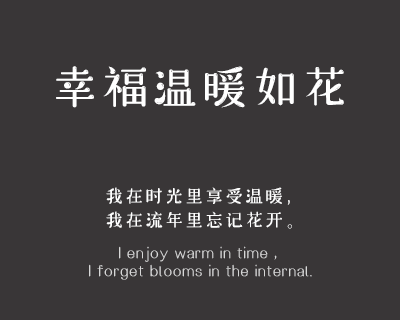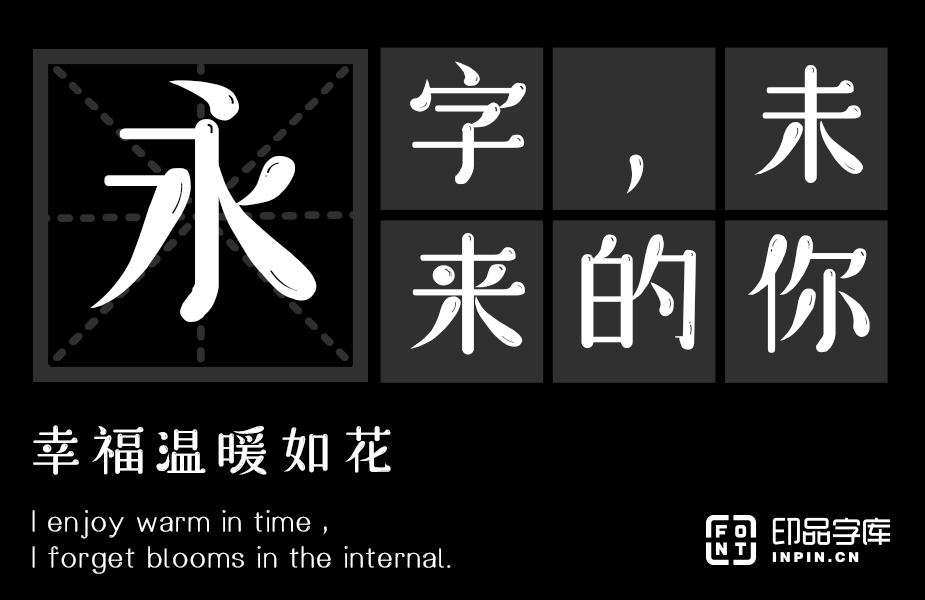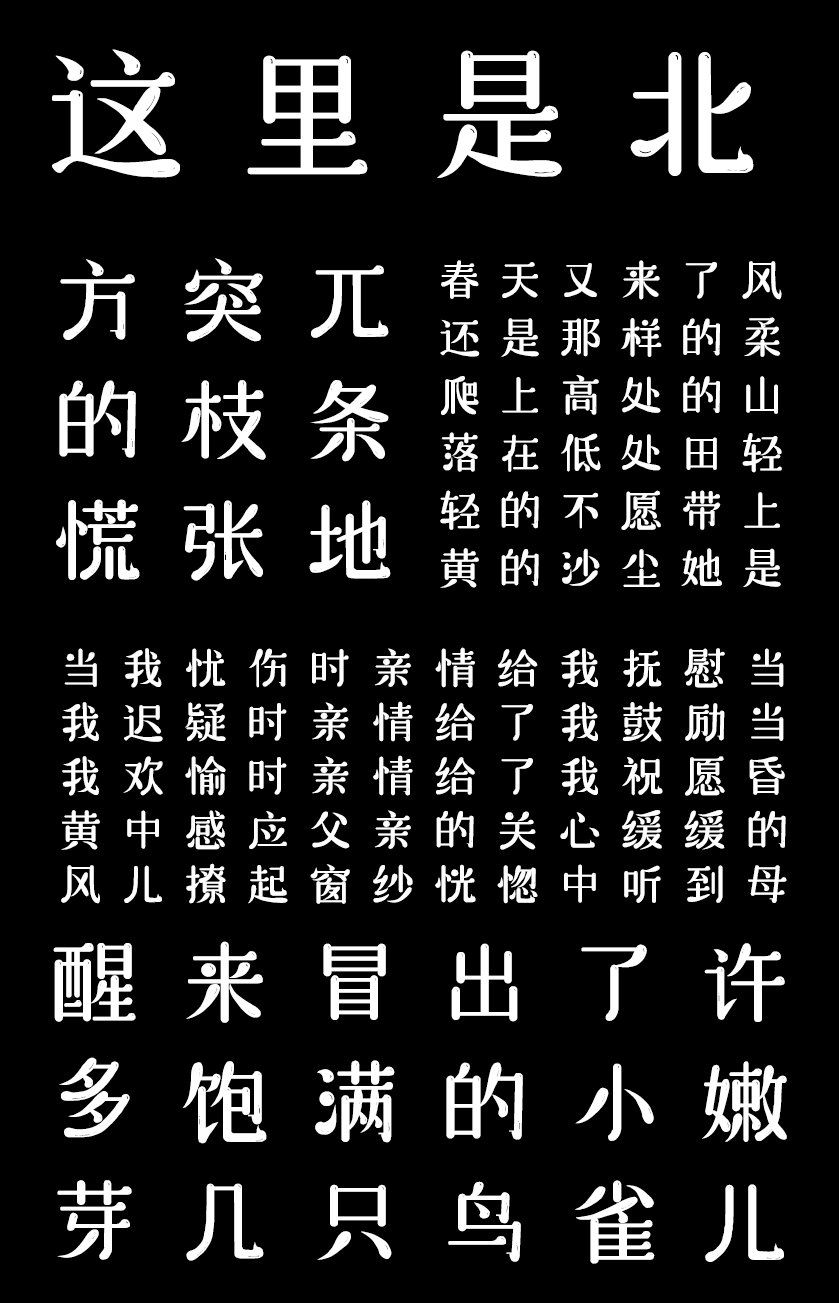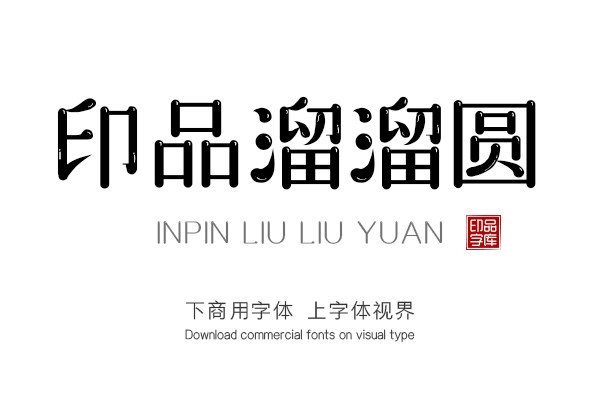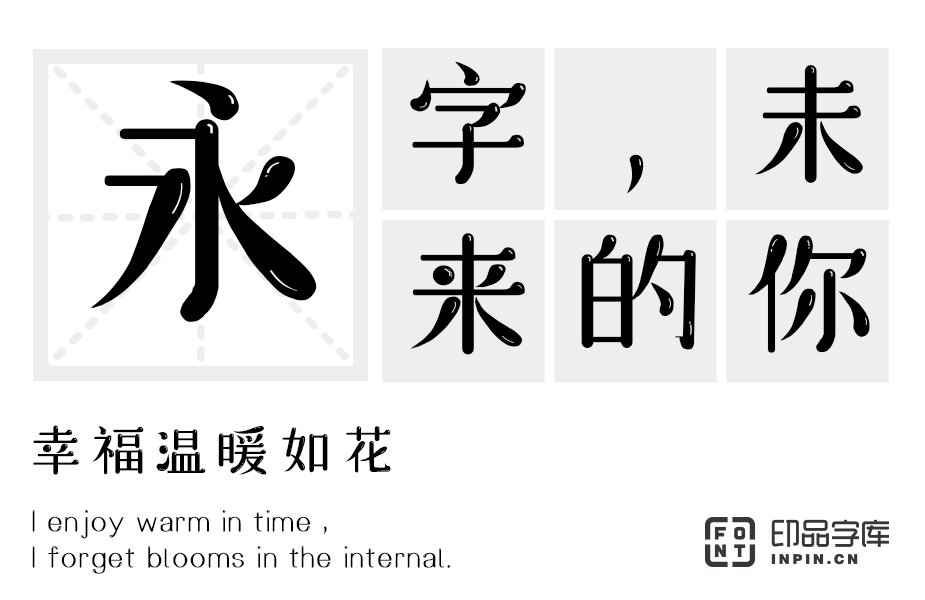
“每逢佳节胖三斤”这种事儿可不只是出现在人身上,瞧这字儿,吃的圆溜溜的,圆圆惹人爱,愿得你喜欢。单字授权
印品溜溜圆,整体圆润饱满,笔画较粗狂,字体内部空间较小,笔画末端做圆弧状处理,朴拙中不失灵动,具有极强的时尚感。字体笔触粗狂厚重,雄阔严整,笔画起承顿挫,飘逸流畅,朴拙中不失灵动;重心一致,结构规整,重心稳定,曲线分明充满张力,整体略显厚重。字体笔划粗壮有力,撇捺等笔画不尖,笔画末端做圆弧状处理,细腻出彩的笔画特点让字形整体更加刚毅,充满力量。圆圆惹人爱,愿得你喜欢。印品溜溜圆适用于LOGO、广告、包装印刷、动漫、影视等场景。